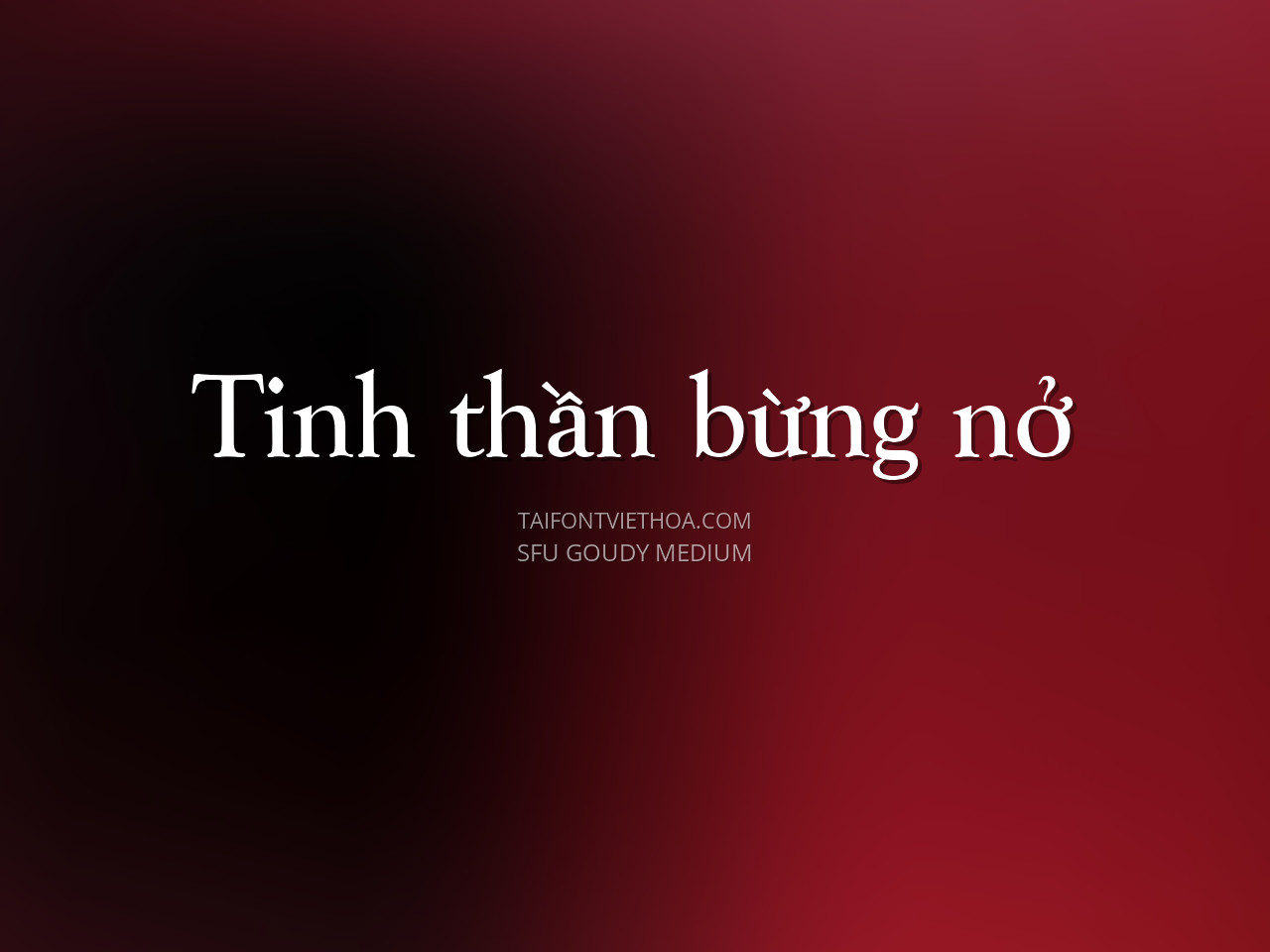
Font việt hóa SFU Goudy
Giới thiệu về font SFU Goudy – Di sản serif kinh điển mang vẻ đẹp học thuật và truyền thống
SFU Goudy là phiên bản Việt hóa của kiểu chữ Goudy Old Style – một trong những font serif kinh điển của thế kỷ 20, được thiết kế bởi Frederic W. Goudy vào năm 1915. Font gốc do hãng American Type Founders phát hành và đã trở thành biểu tượng trong thiết kế sách, báo in, tài liệu học thuật và các ấn phẩm truyền thống. Goudy mang đến cảm giác cổ điển, thanh lịch và dễ đọc, phù hợp với những dự án cần thể hiện chiều sâu văn hóa và sự chuẩn mực về hình thức.
Phiên bản SFU Goudy được Việt hóa đầy đủ với hệ thống dấu tiếng Việt hoàn chỉnh, giữ nguyên tinh thần nghệ thuật của bản gốc. Taifontviethoa.comđã lựa chọn và chia sẻ font này như một phần trong bộ sưu tập font serif cao cấp, giúp người dùng Việt Nam tiếp cận dễ dàng với các kiểu chữ chuẩn mực, có bề dày lịch sử và khả năng ứng dụng rộng trong thiết kế chuyên nghiệp.
Đặc trưng thiết kế cổ điển và ứng dụng đa dạng của SFU Goudy
SFU Goudy nổi bật với các nét chữ có chân mềm mại, độ tương phản giữa nét dày và nét mảnh vừa phải, mang lại cảm giác gần gũi và trang trọng. Các ký tự có dạng tròn trịa, có phần mở rộng ở đầu nét tạo ra hiệu ứng thị giác ấm áp và dễ đọc. Font hoạt động tốt cả trong đoạn văn dài lẫn tiêu đề trang trọng.
Ứng dụng lý tưởng: sách in, báo chí, luận văn, thiết kế nhận diện thương hiệu cổ điển, sản phẩm mang tính truyền thống hoặc mang hơi hướng châu Âu. Ngành nghề phù hợp: xuất bản, giáo dục, luật, tôn giáo, văn hóa, bảo tàng, mỹ thuật và các lĩnh vực cần truyền tải giá trị lịch sử và sự tin cậy.